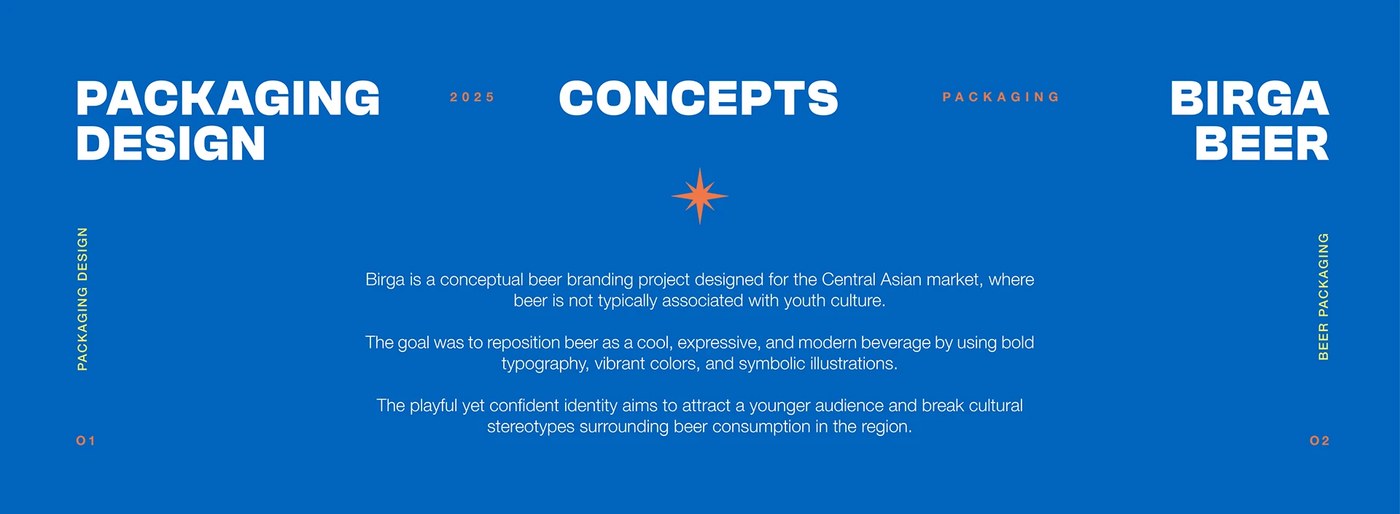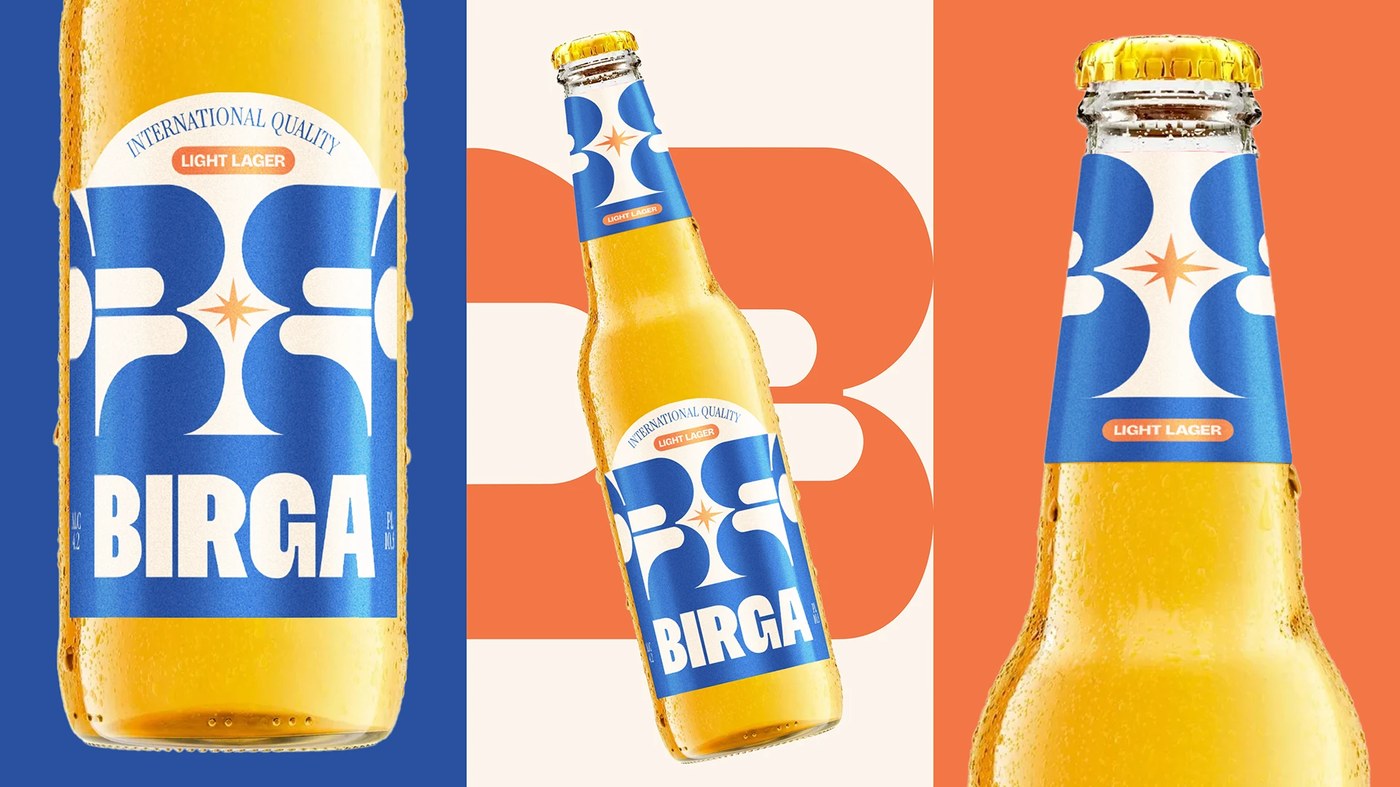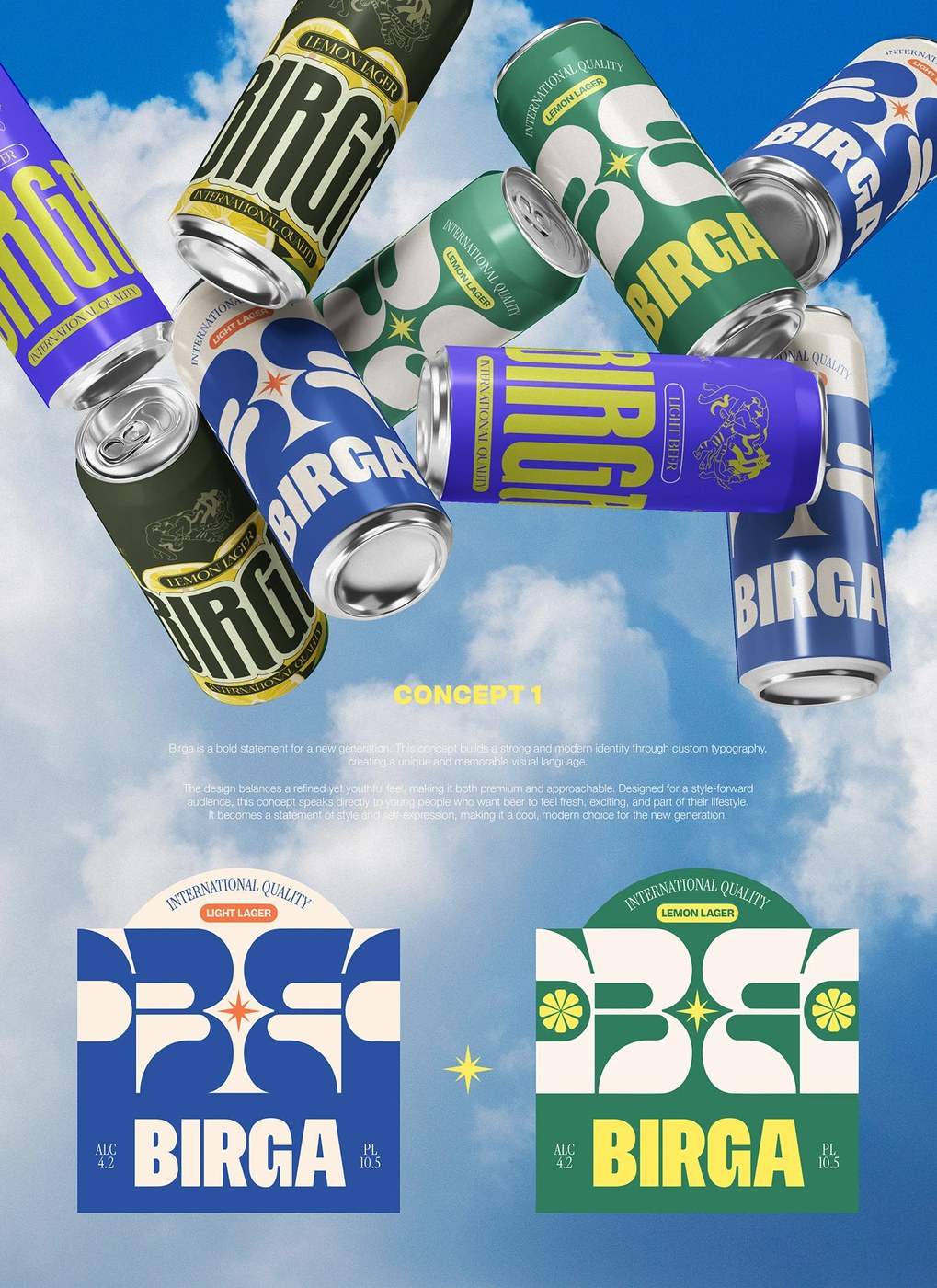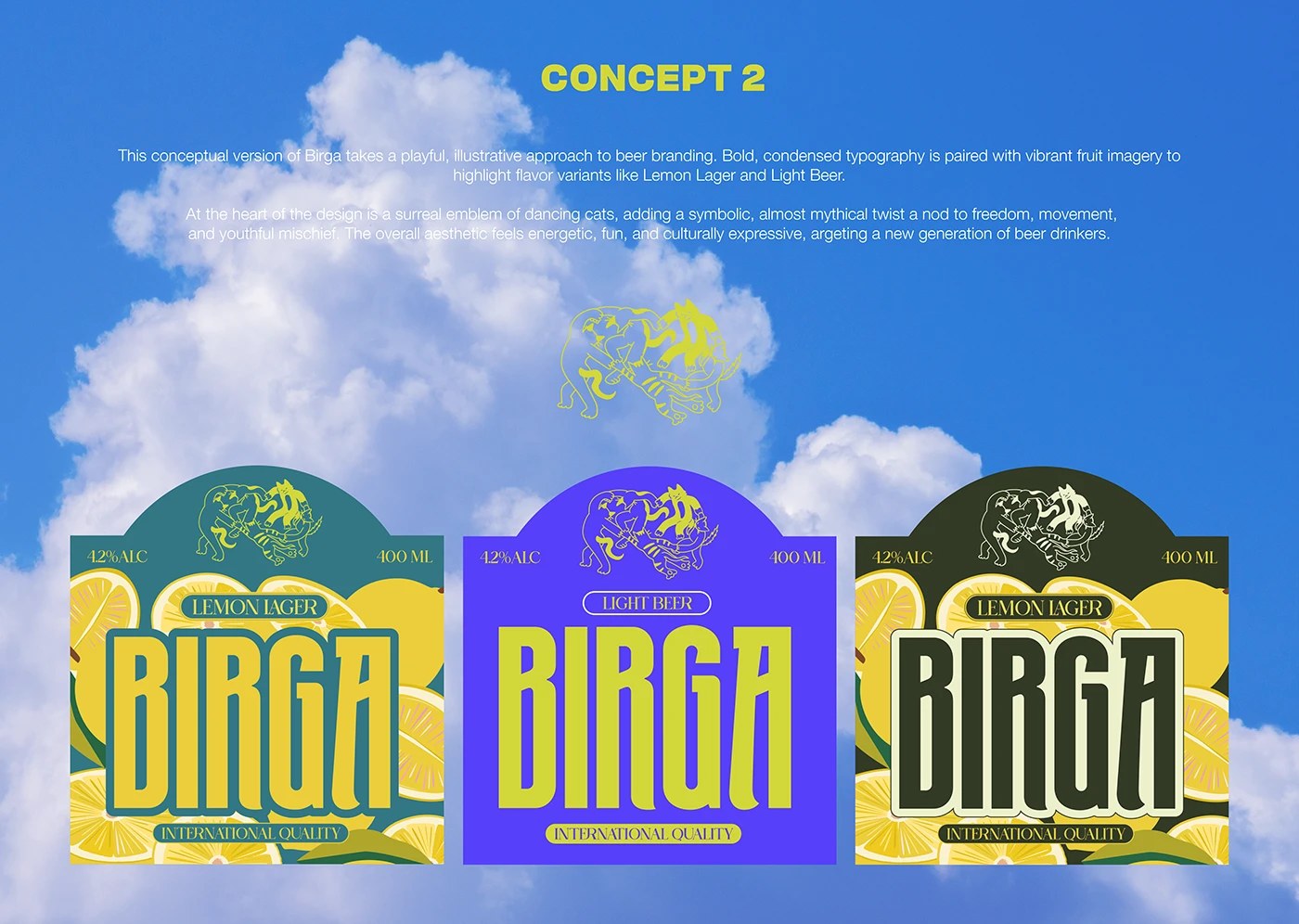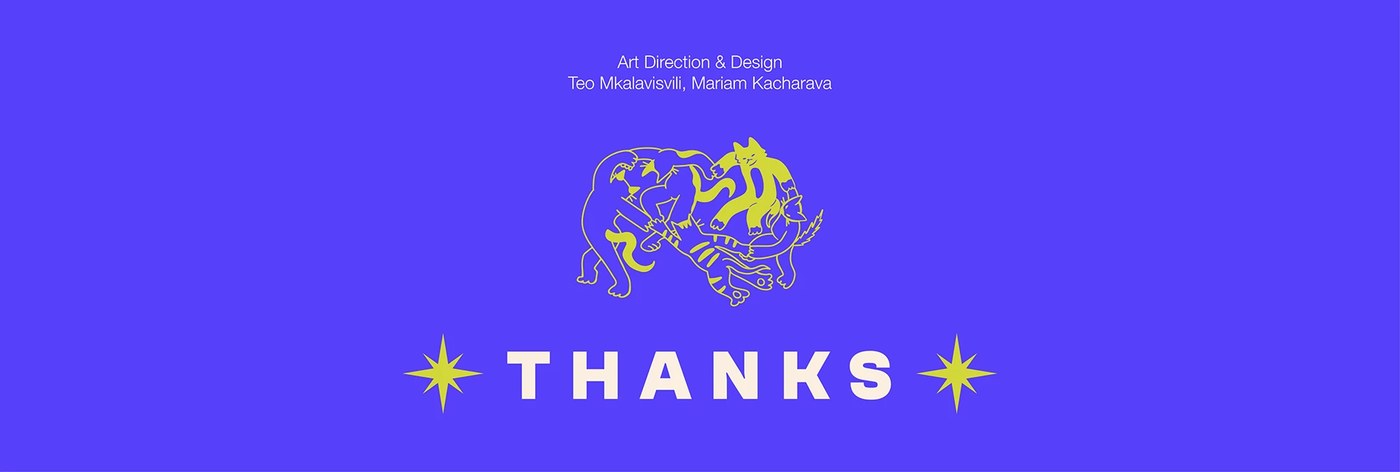
El diseño del packaging de cerveza Birga apuesta por nuevos mercados con tipografía atrevida
El diseño del envase de cerveza de FCB Artgroup Tbilisi utiliza una tipografía atrevida para reposicionar la cerveza Birga en un mercado de Asia Central donde la cultura aún se está formando.
La decisión central es la escala. La letra “B” ocupa aproximadamente el 70% de la altura de la etiqueta, no como decoración, sino como imagen principal. En un trío de botellas en naranja saturado, las letras se leen con las proporciones de un tablero publicitario, actuando como textura de fondo y amplificador de marca en el mismo marco. Cada sabor tiene su propia paleta de dos colores: azul cobalto y crema para pale ale, chartreuse para limón, pero ambos sabores mantienen la misma tipografía audaz: “CALIDAD INTERNACIONAL” en una parte superior curva, pastillas aromatizadas debajo y “BIRGA” en una tapa ancha blanca en la parte inferior. Este diseño de empaque de cerveza no cambia de forma para diferenciar el producto; la tipografía en negrita funciona.
Las fuentes en negrita son el poder de la marca en el diseño de envases de cerveza
Un lugar donde el diseño del envase de cerveza rompe con su propia geometría es en el soporte de 4 piezas. La ilustración del gato bailando es un contorno dibujado a mano, suelto e irreverente, impreso a sangre completa detrás del tipo de letra. Este contraste se ha ganado su lugar: la tipografía atrevida genera debate; los gatos dan permiso. El diseño del envase de cerveza, que tenía que reposicionar una categoría entera, no podía dejar que la ilustración hiciera el trabajo pesado: FCB Artgroup Tbilisi sabía exactamente dónde usarla.